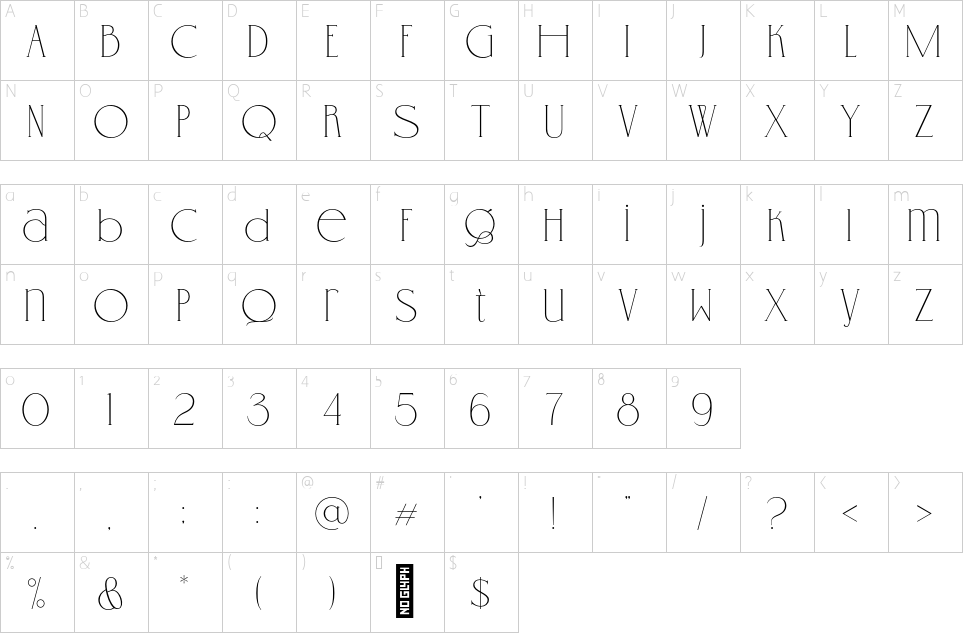
A fonte Gallerya está disponível para download gratuito tanto no Windows quanto no Mac. Esta elegante e moderna font foi projetada por Brandsemut. Com seu design minimalista e claramente legível, Gallerya é uma opção ótima para designers que procuram uma fonte de qualidade sem gastar muito. Embora não tenha sido desenvolvida especificamente para uso em portfólios ou apresentações, a Gallerya pode ser usada em qualquer projeto onde o estilo limpo e profissional seja desejado. Com um download total de 1,775 vezes, é evidente que esta font tem a simpatia do público, oferecendo uma combinação perfeita de beleza visual e funcionalidade prática.